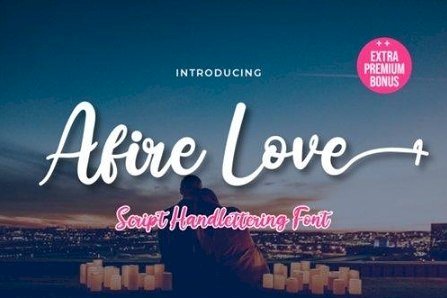
Afire Love Font
Afire Love é uma fonte manuscrita fluida, descrita por um toque elegante, perfeita para seus projetos favoritos.
Afire Love Font
Apaixone-se por seu estilo incrivelmente distinto e atemporal e use-o para criar designs espetaculares!